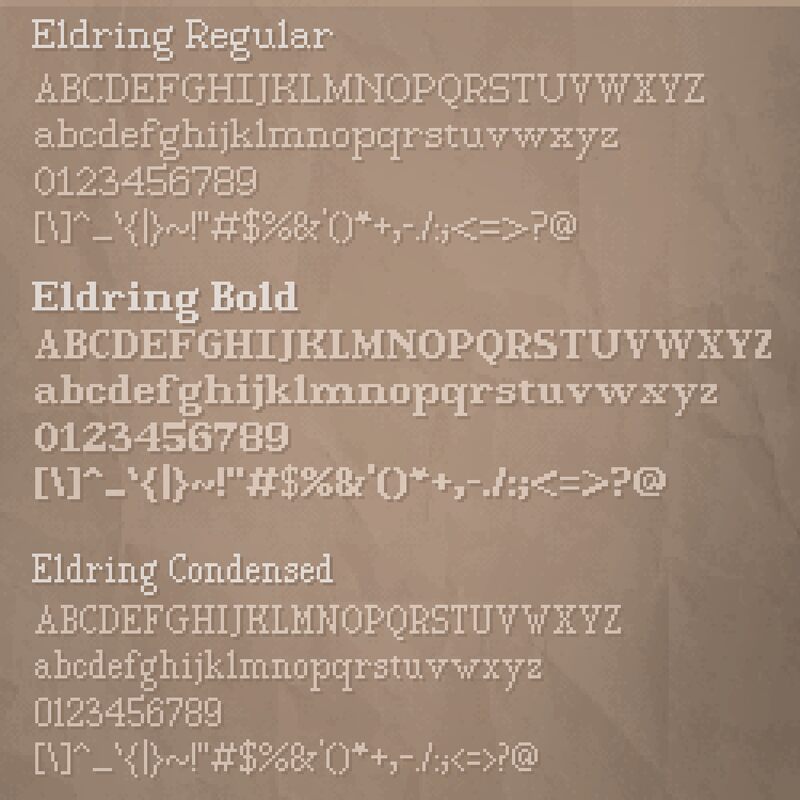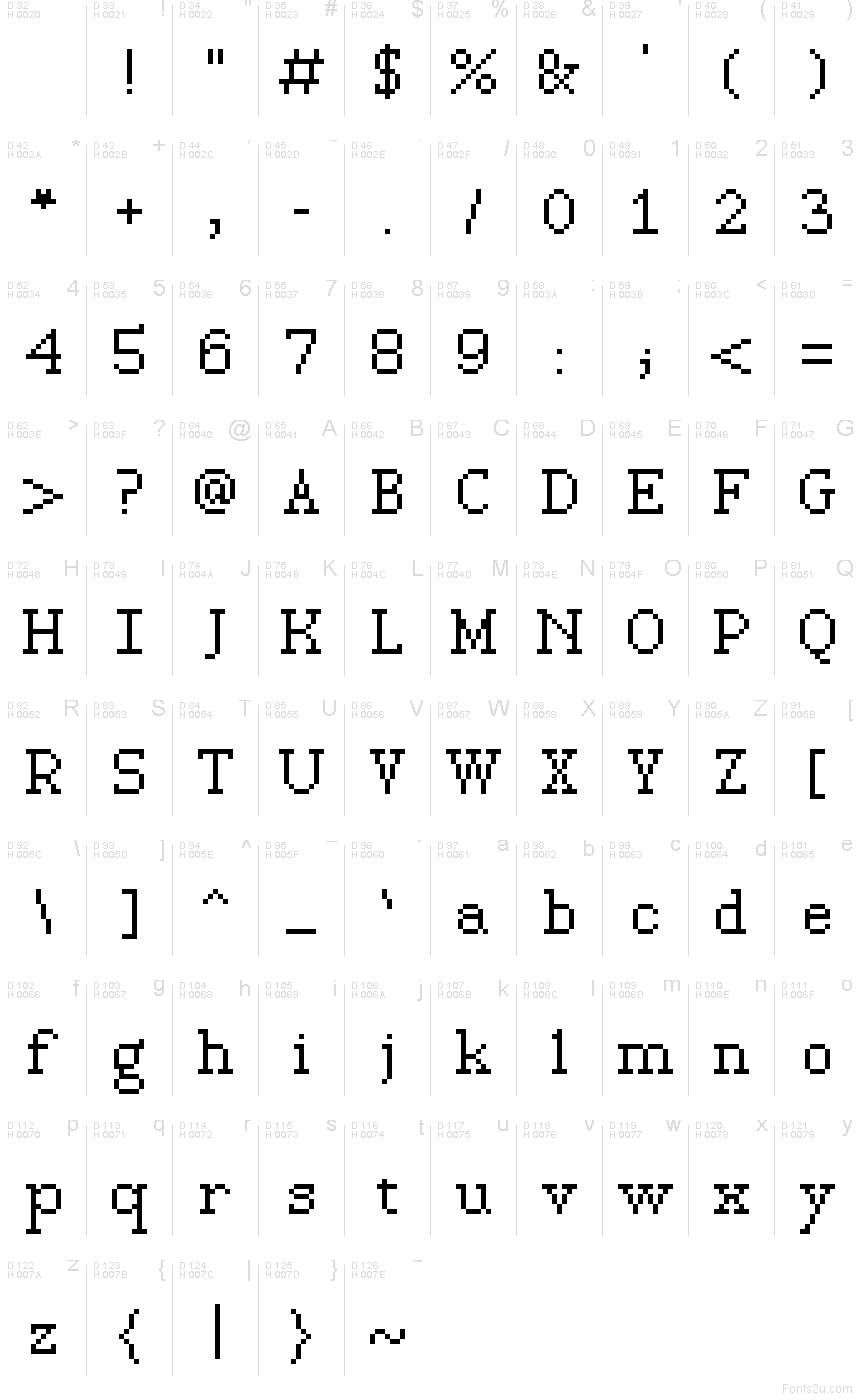
Eldring od Skeddles je bezplatné pixelové písmo složené z ostrých, čtvercově zakončených tahů, čistých pravých úhlů, nepravidelných šířek a volné siluety raných počítačů. Otevřená, kosterní písmena využívají prudké zářezy a schodovité spoje.
Schémata obvodů a herní grafika v nízkém rozlišení sdílejí jeho modulární geometrii, díky čemuž je toto písmo vhodnou volbou pro úvodní obrazovky retro her, technologické plakáty, grafiku elektronické hudby a branding arkádových akcí. Tyto opakující se mezery a blokovité rohy se mohou stát součástí panelů rozhraní nebo ilustrací inspirovaných bludišti a dodávat merchandise přesvědčivý odkaz na ranou digitální estetiku.